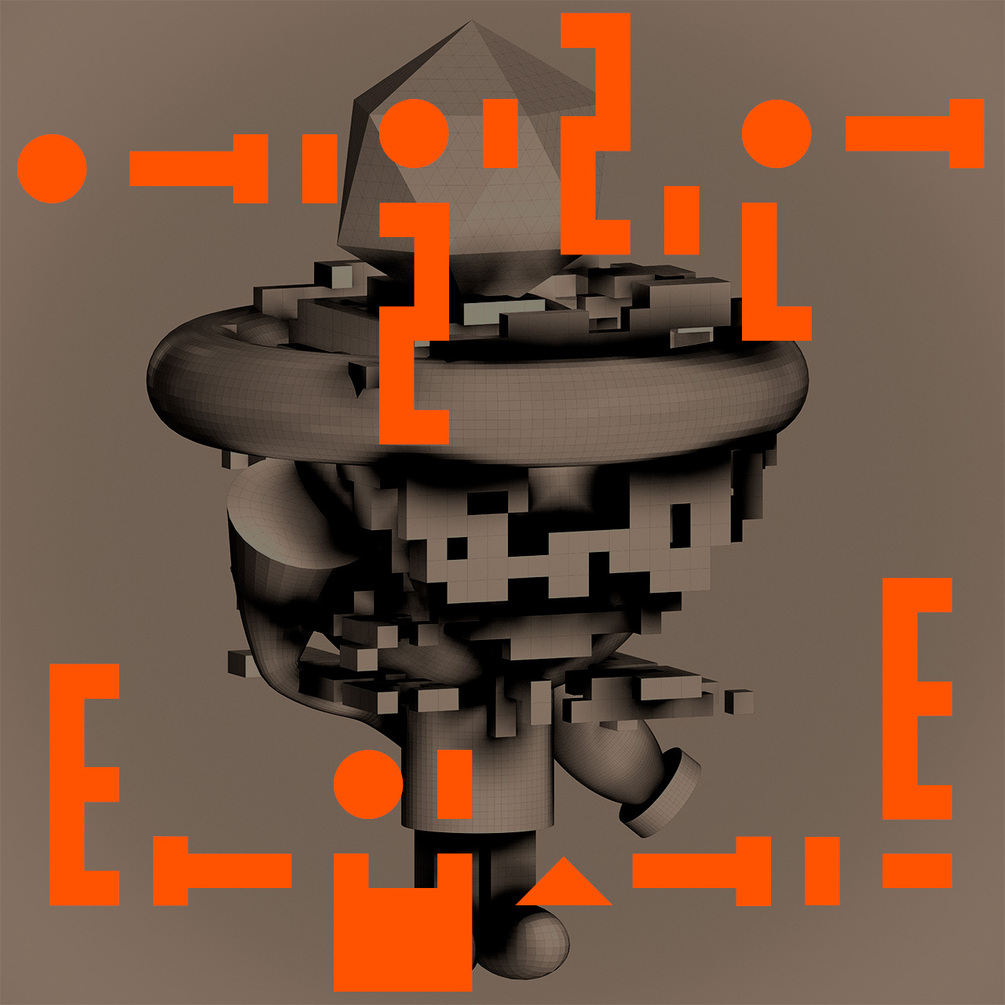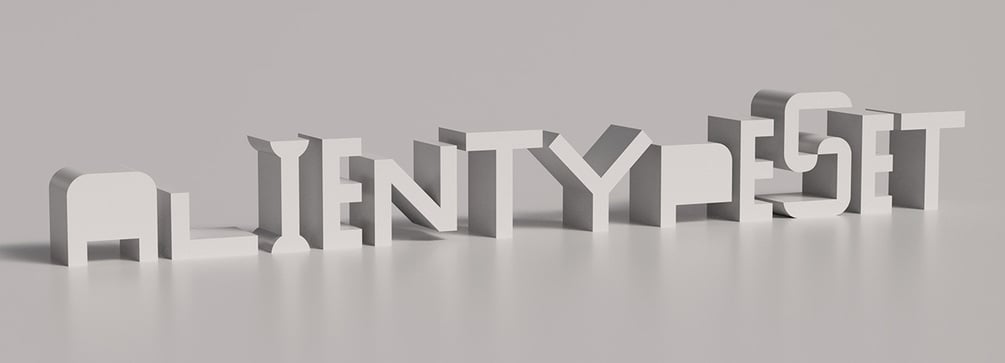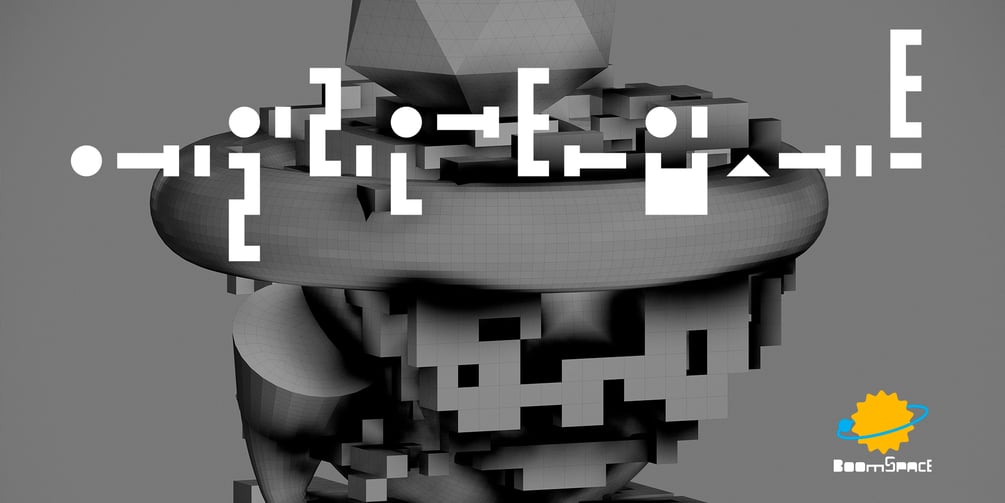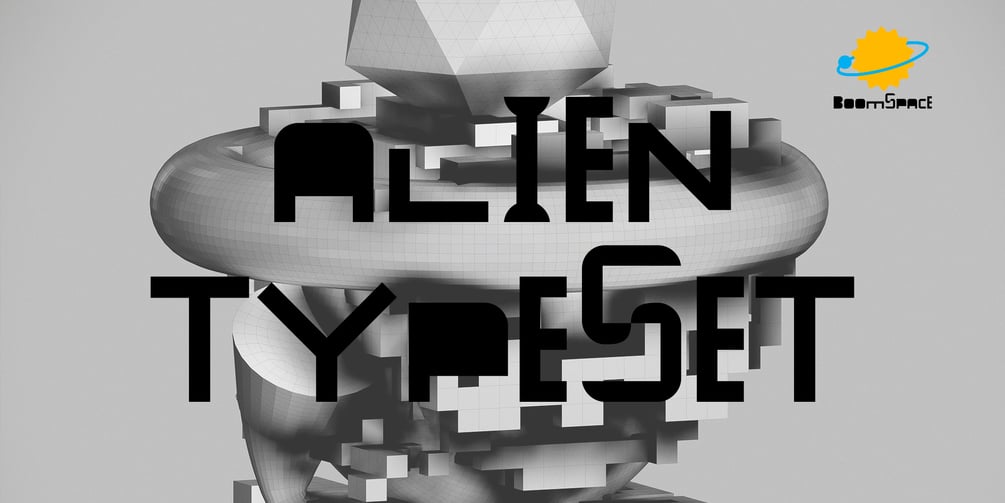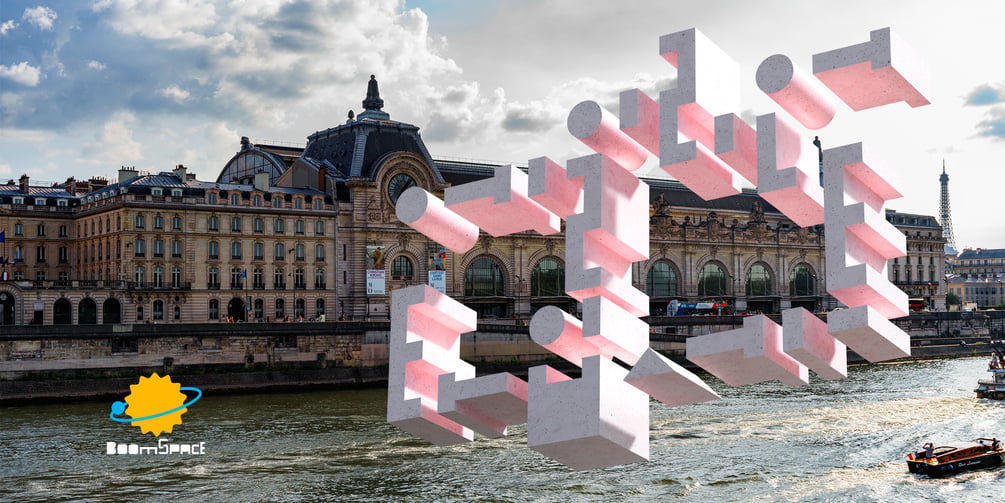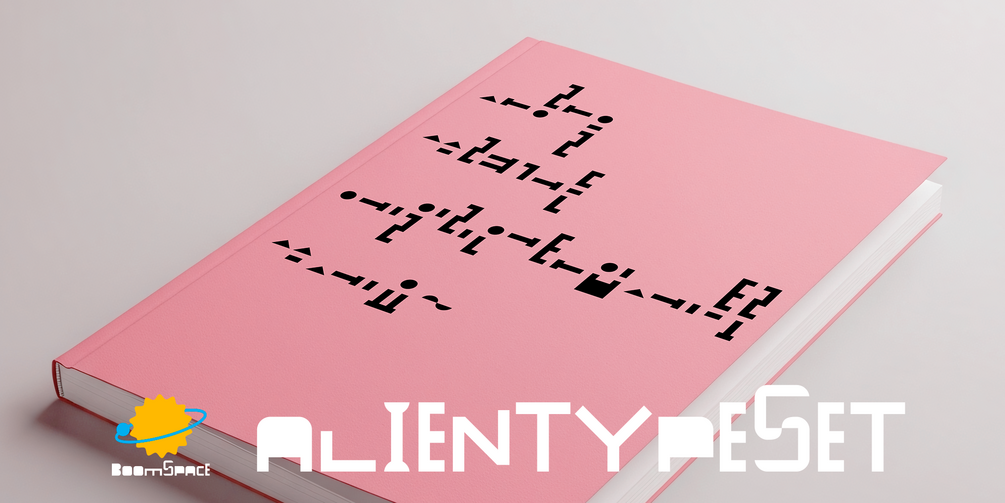
ALIENTYPESET
에일리언타입세트 ALIENTYPESET
2024년 한글날 578돌을 기념해 새로운 한글 서체를 만들었어요. 서체 이름은 ‘에일리언타입세트 ALIENTYPESET’인데 제목 그대로 외계 문자라는 뜻을 품고 있습니다. 그래서인지 이 서체는 매우 읽기 힘듭니다. 서체 디자인 역사상 가독성을 추구하면서도 동시에 가독성을 내다 버린 희한한 서체가 되지 않을까 생각합니다. 어느 모로 보건 비가독형 글꼴이라는 게 넘버 1 특징이에요. 서체 제작에 사용된 몇 가지 규칙을 살펴보면, 우선 첫째로, 음절 본질을 유지하는 범위 내에서 긴 획은 짧게, 짧은 획은 길게 반대로 디자인했습니다. 둘째, 선으로 이루어진 자음을 면으로 변형하기도 했으며, 셋째, 탈 네모꼴 서체인 이유로 작은 글자 크기를 일반 서체 크기 수준으로 키우기 위해 상하단 디자인 범위를 넘기도 했습니다. 따라서 어떤 경우에는 위아래 행과 글자가 겹칠 가능성도 없지 않아요.
만약 외계 문자가 정말 있다면, 우린 아마도 이해하기는커녕 소리 내어 읽기도 힘들지 않을까요? 바로 이 에일리언타입세트 서체가 그렇습니다. 하지만, 그렇다고 해서 정말 아무도 읽을 수 없는 서체를 만든다면, 그게 무슨 의미가 있을까요. 그래서 이 서체는 특이하게도 서체 사용 권장사항이 있는데 이를 어느 정도 지킨다면 읽을 수야 있습니다. 글자 크기를 24포인트, 행간을 170퍼센트 이상으로 설정하면, 그나마 없는 가독성이 아주 조금 생기며, 윗줄 아랫줄 글자가 겹치는 상황도 벌어지지 않습니다. 물론 이 서체 특징인 비가독성에 마음을 빼앗겨 권장사항을 가뿐히 무시하고 횡설수설 텍스트를 흩뿌린 듯한 디자인을 하면, 진정 외계 글자나 큐알 코드를 보는 듯한 타이포그래피 결과물을 얻을 수도 있어요.